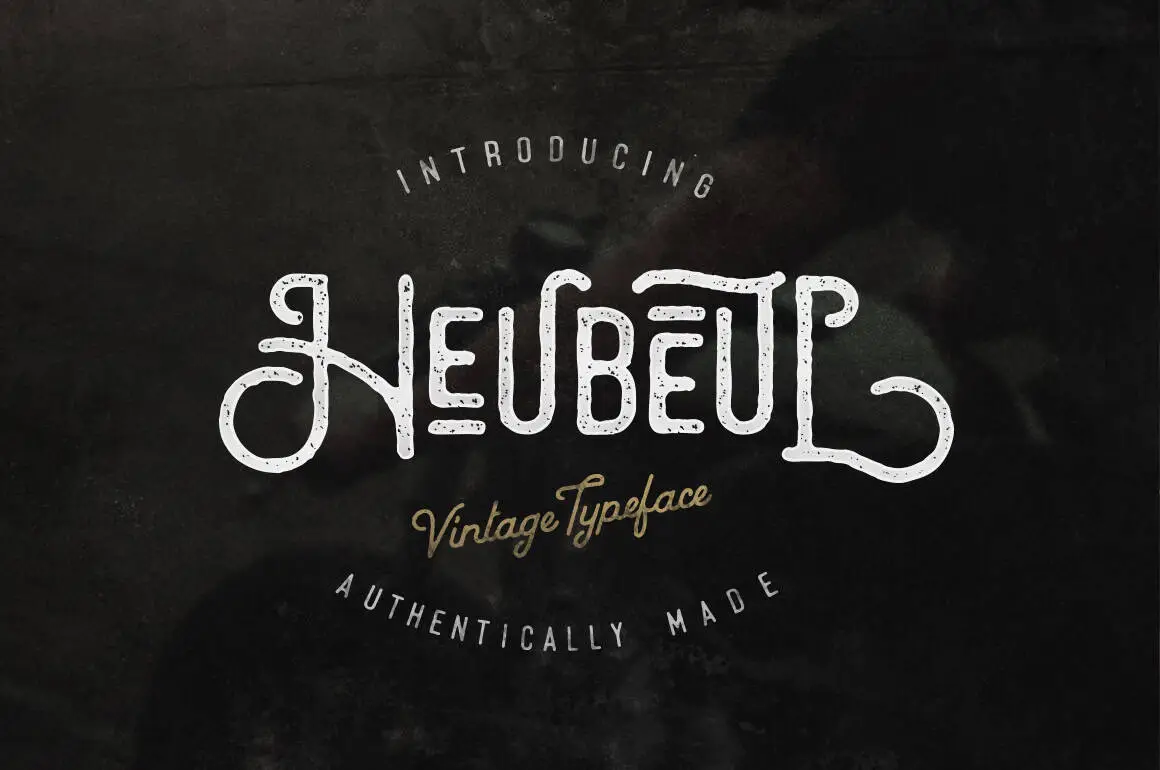
A Heubeul Typeface é uma fonte retro elegante criada pelo font designer Hamilton. Com seu charme vintage e linhas delicadas, a Heubeul oferece uma experiência visual única que remete à memórias nostálgicas de computadores antigos. Este design, repleto de carácter, foi projetado para quem aprecia o clima retro mas não abdica da elegância moderna. Em uma era onde muitas fontes contemporâneas se tornaram tão comuns, a Heubeul se destaca por sua riqueza de detalhes e sutileza, proporcionando um toque diferente aos documentos e design gráfico que usa. Para quem valoriza as antigas tecnologias no formato digital da atualidade, esta fonte retro é uma escolha perfeita.